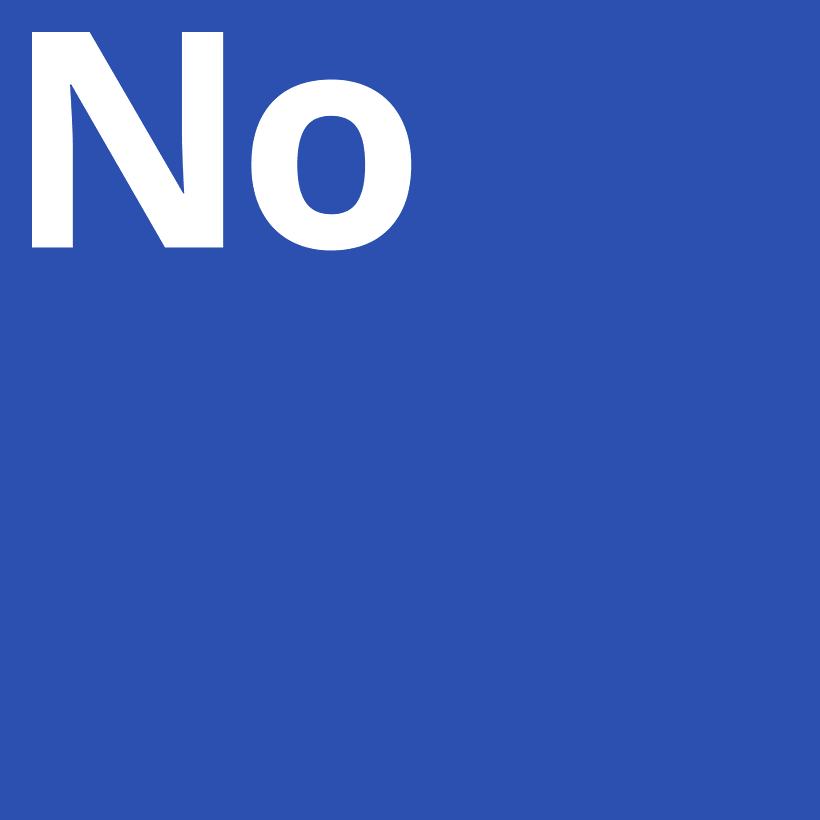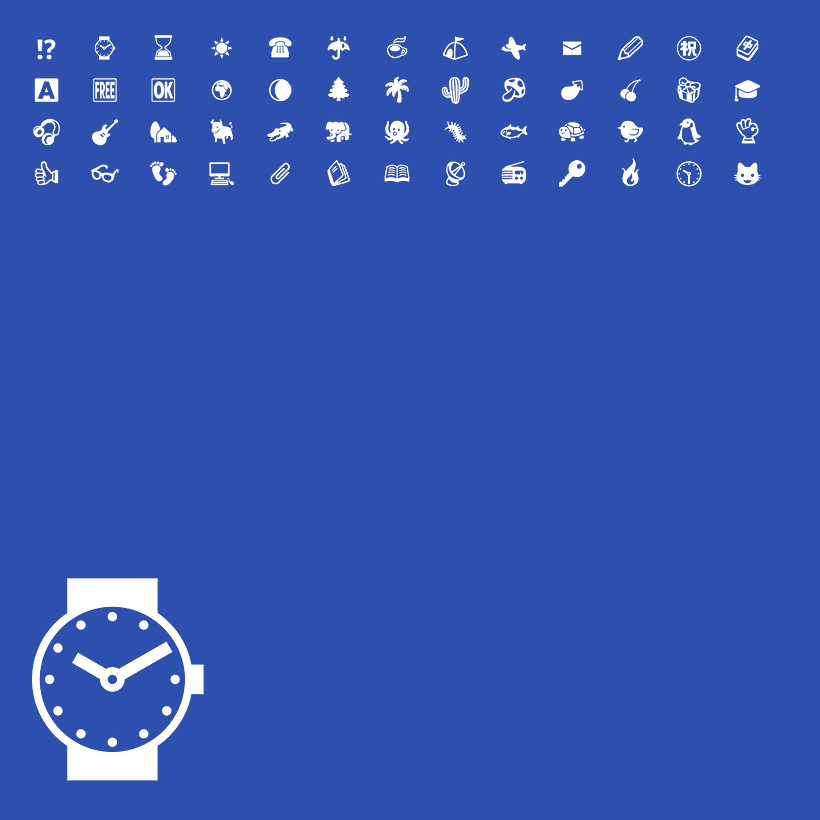
Noto, la tipografía para todos los idiomas del mundo
Probablemente habrás notado que, cuando tu ordenador, móvil o tablet, no es capaz de leer algún carácter de un texto lo transforma en un pequeño rectángulo.
A esa forma de representar un error en la tipografía se le ha llamado "tofu" por su similitud con el alimento y la manera en que se suele cortar. De la contracción de "no more tofu" nace Noto, la nueva tipografía universal de google que recoge 110.000 caracteres correspondientes a 800 lenguas distintas, es decir, cada uno de los símbolos del estándar de Unicode.
Con Noto, google pretende dar uniformidad a las tipografías y evitar que aparezcan esos recuadros cada vez que un glifo no está disponible.
En algunas lenguas no es tan común toparse con "tofus", pero existen muchas variables que crean este error en algunos idiomas. El árabe y algunas lenguas de la India, tienen muchas variaciones o admiten diferentes reordenaciones según el texto que los acompañe; como consecuencia, se necesitan cientos de profesionales para testear cada uno de los idiomas, haciendo el proyecto inmenso.
La principal preocupación de google a la hora de desarrollar Noto, un proyecto en el que llevan trabajando 5 años, es la de hacer que la tipografía funcione igual para todos los idiomas, logrando que no existan diferencias notables visualmente hablando a la hora de cambiar de una lengua a otra. Hasta ahora, cambiar de un alfabeto a otro significaba obtener un aspecto visualmente diferente de una a otra, con Noto la uniformidad está asegurada.
Noto es un sistema de código abierto y google se ha comprometido a mantenerla actualizada e incluir cada carácter nuevo que se añada a Unicode.
De esta manera se pretende preservar las lenguas y equipararlas todas por igual, sin dar mayor preferencia a aquellas que son utilizadas en detrimento de aquellas más minoritarias.